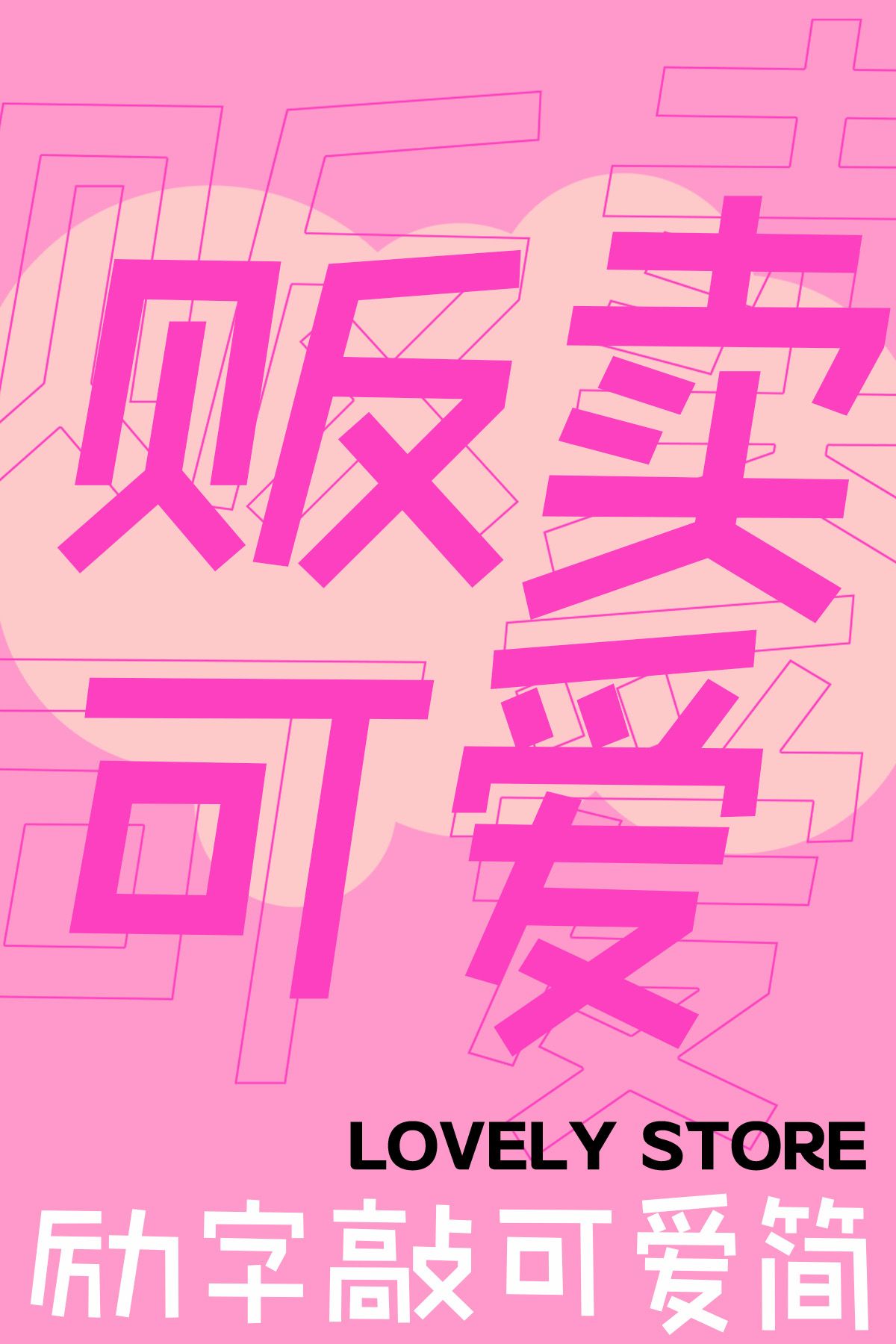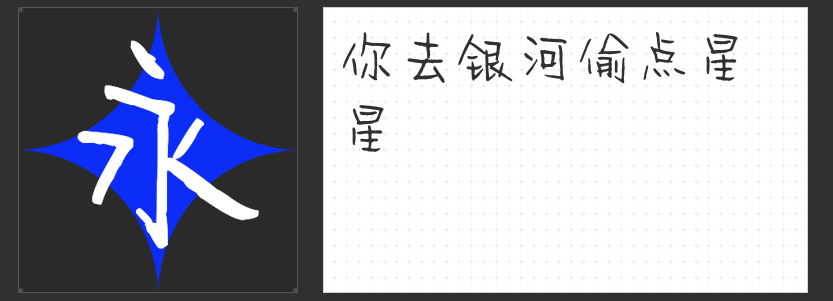
INS风清新可爱手写字体推荐:让你的文字也“萌”起来
在追求个性化和视觉美感的今天,字体选择成为了展现品牌或个人风格的重要一环。INS风以其清新、自然的特点深受大家喜爱,而手写字体更是增添了一份亲切与温暖。今天,就为大家推荐四款INS风清新可爱的手写字体,让你的文字也“萌”起来!
这款字体是专为满足更多展示效果而设计的手绘字体,整体舒适自然,笔画童稚可爱。当卡通元素与字体相遇,两者不仅相互匹配,更达到了相得益彰的效果。无论是用于标题、正文、宣传语还是品牌的标准用字,MyFont凌渡未卜简都能轻松驾驭,为你的作品增添一抹童趣与活力。
略带俏皮,充满趣味与想象的励字敲可爱简,以其圆润的手写线条和独特的省略笔画设计,营造出一种用心书写的随性。这款字体在保留辨识度的前提下,通过简单明快的线条和独特的形式,让字体更具手绘感,带来手写的柔软和温暖。无论是用于社交媒体、海报设计还是其他创意场景,都能让你的文字瞬间“敲可爱”。
三、字恋狂白日梦简
如果你想要一种如梦似幻的感觉,那么字恋狂白日梦简绝对是你的不二之选。这款字体以凌乱的线条笔画,仿佛在时光中穿梭,营造出一种梦幻般的氛围。它非常适合用于绘本、漫画等场景,让你的作品充满想象力和艺术感。
四、字恋狂嗨玩简
最后为大家推荐的是字恋狂嗨玩简,这款字体以其粗壮的笔画和方块字形,像积木一样可爱而笨拙。重心靠下的设计,让整个字体给人一种笨拙可爱的感觉。无论是用于儿童教育、游戏设计还是其他需要活泼氛围的场景,字恋狂嗨玩简都能让你的文字更加生动有趣。
以上四款INS风清新可爱的手写字体,每一款都有其独特的魅力和应用场景。快来选择一款你喜欢的字体,让你的文字也“萌”起来吧!